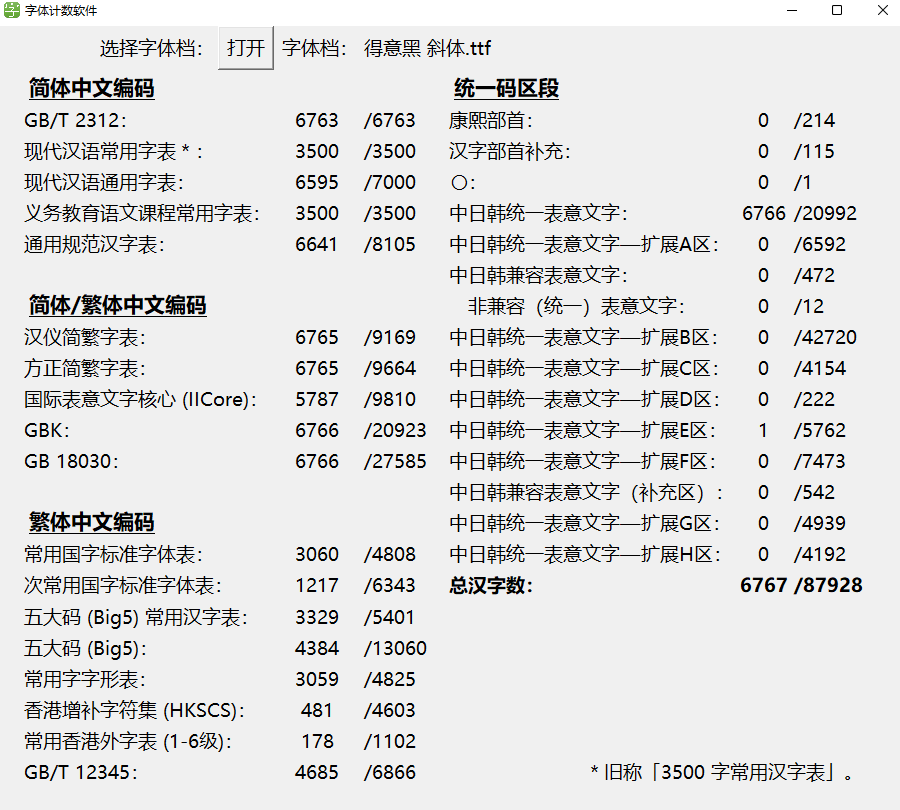
得意黑:oooooohmygosh发布的第一款免费商用字体
字体作者:oooooohmygosh (中国大陆) 字体字重:1个
这是我以oooooohmygosh身份发布的第一款字体,11月15日正式开源发布,大家可以免费商用无任何限制,也可以修改创作。说个不太切实际的梦想,我希望以这个身份发布的所有作品,都是开源或者公益的。 这套字经过我和其他字体设计师伙伴们一年多的波折,终于要面世了。这款字虽然是美术字,但却是一个有挑战的命题。因为它有三个特征「大弧线、窄、斜」,每一项都很难做好。更何况把它们仨融合到了一起,还要去追求稳、匀、整……
• 得意黑 Smiley Sans 现支持《通用规范汉字表》中全部 8105 个汉字 🎉
• 得意黑 Smiley Sans 正式发布!🎉
从这字体作者得到的信息,这字体支持部分生僻字,如喆、乸、冚、俶、冏、囧、凪等
最好补充一下繁体和生僻字
这套字体不倾斜或许更好看点?感觉现在中文字体开始走入斜体的怪圈了……
• oooooohmygosh说目前网上还没有一款开源的中文美术字体(因为美术体更容易卖出好价格),因此他和团队在设计得意黑这款字体时特意做成斜体,以凸显差异性。当然如果你特别在意的话可以在PS,AI里把文字做一定的反向倾斜或者在原有字体的基础上再做一个“扶正”后新的字体。
• 官方有做正体和粗体的计划